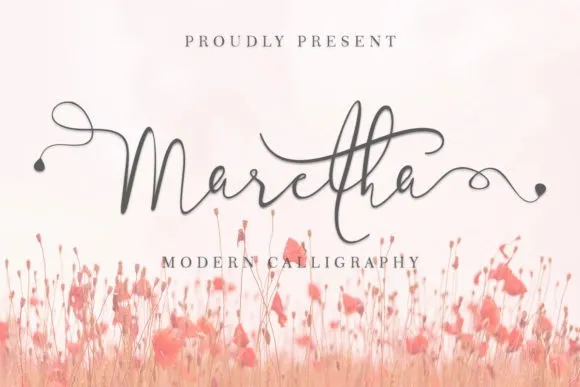
Maretha Calligraphy Font
A fonte “Maretha Calligraphy Font” é uma criação única e encantadora que combina elegância antiga com a modernidade atual. Esta fonte script é versátil, capaz de moldar qualquer projeto gráfico ao seu estilo. Ela abrange desde cartões de cumprimentos até cabeçalhos chamativos, permitindo que você personalize suas mensagens de maneira única e emocionante. Adicionada a este conjunto de recursos incríveis está o designer, yogaletter6, que compartilha seu amor pelo mundo do yoga ao criar esta fonte. Com seu desenho autêntico, “Maretha Calligraphy Font” oferece um toque romântico para seus próximos projetos gráficos. Ideal tanto para criações de casamento quanto para arte em cartões de presente, esta fonte é uma escolha perfeita para deixar sua próxima publicação social ou cartão de cumprimentos mais apaixonada e única. Já imaginou o impacto que essa fonte poderia ter no seu próximo trabalho gráfico? Ela é capaz de fazer as palavras se tornarem obras de arte, trazendo vida e emoção à sua mensagem. Seja para cartões de aniversário delicados, letras em blogs ou até mesmo posts nas redes sociais, “Maretha Calligraphy Font” tem tudo o que você precisa para deixar suas criações ainda mais memoráveis e encantadoras.